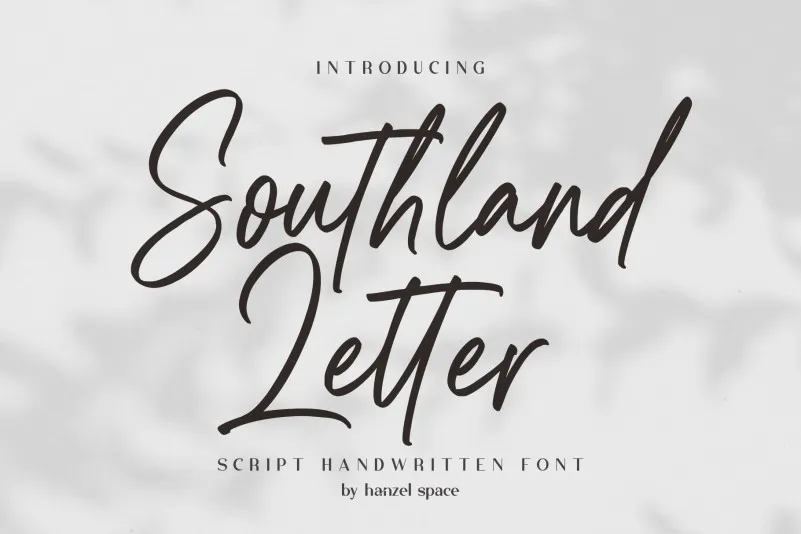
Southland Letter Font – Download Grátis
A Southland Letter é uma fonte script que oferece um charme único e elegante, característica marcada por sua grossura apreciável. Conhecida pelo seu uso profissional, esta fonte se destaca não apenas para marcas e mensagens de casamento, mas também para anúncios de marca, slogans, cartas pessoais, até mesmo para rótulos ou logotipos. Ela traz um toque autêntico ao design gráfico que faz dela uma opção versátil para designers de todo o mundo. Seja você criando uma identidade visual profissional ou adesivos personalizados, a Southland Letter é uma escolha inteligente que valorizará sua marca.